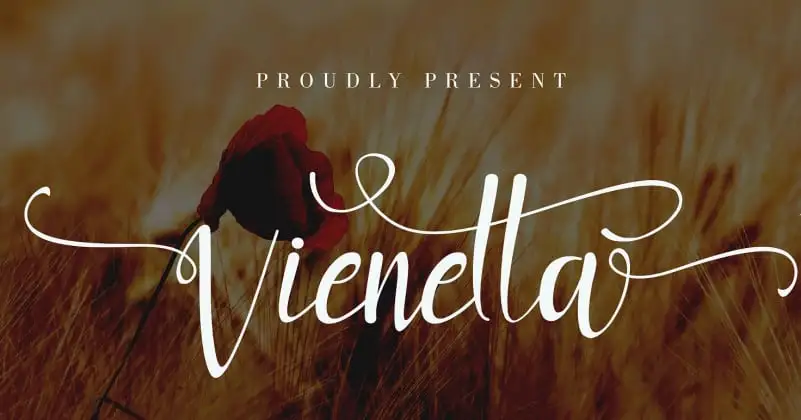
Vienetta Calligraphy Font – Download Grátis
A Vienetta Calligraphy Font é uma opção perfeita para aqueles apaixonados por elegância e delicadeza na tipografia. Esta fonte retrata a beleza e sofisticação que as chamadas ‘fonts de papel higiénico’ proporcionam, combinando formas arredondadas com um toque romântico. Ela é perfeita para ser usada em festas de casamento tanto no design de cartões de convite quanto pelo planejador da festa e pelos proprietários das lojas florais. Também é uma escolha ideal para quem trabalha nas áreas de maquiagem profissional e fotografia, buscando um touch elegante e romântico em seus projetos. Esta fonte não só adicionará sofisticação a qualquer projeto que você estiver desenvolvendo, mas também manterá o espírito romântico dessas atividades tão importantes no mundo das festas e do entretenimento.